Alude a un trazo decorativo que puede tener un signo. Se relaciona con el concepto de swash, que describe un trazo alargado o exagerado de un carácter (como una cola extendida), que a veces imita una decoración floral o un adorno.
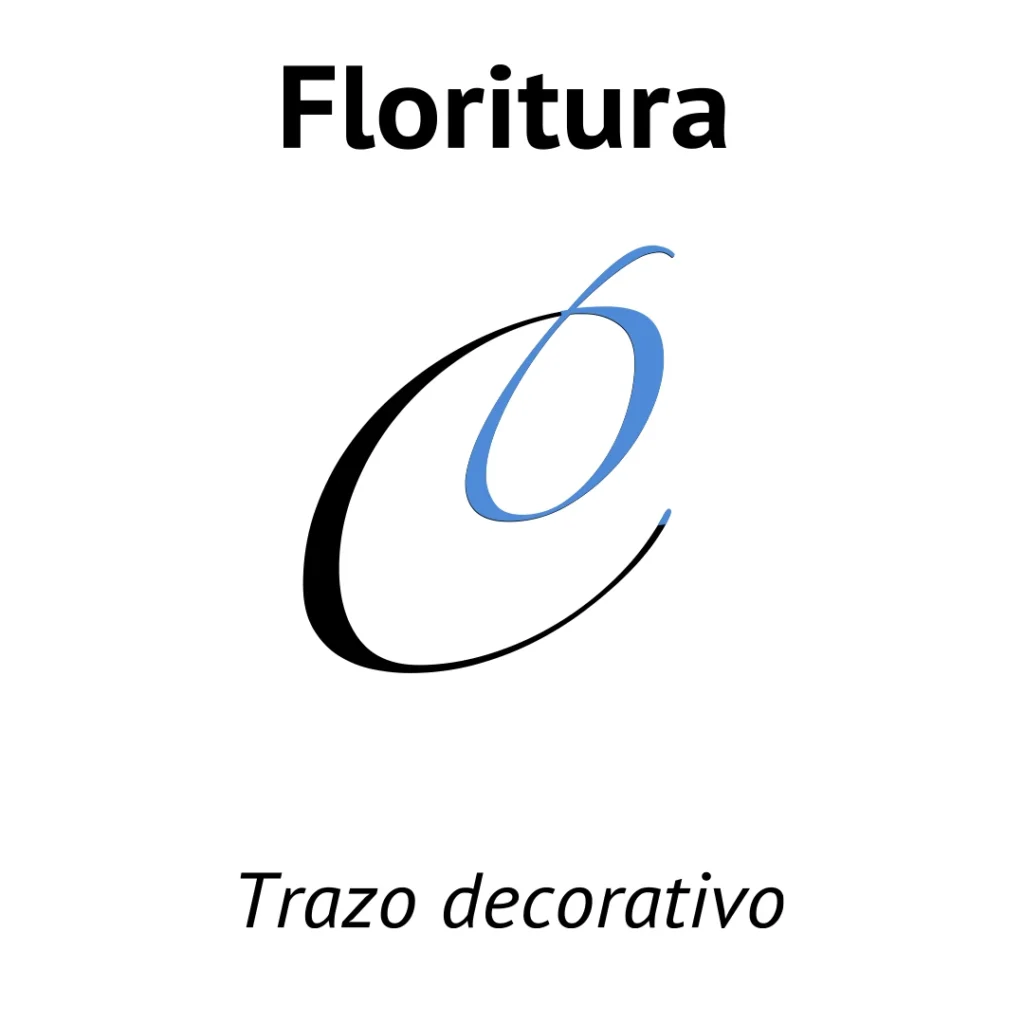
Alude a un trazo decorativo que puede tener un signo. Se relaciona con el concepto de swash, que describe un trazo alargado o exagerado de un carácter (como una cola extendida), que a veces imita una decoración floral o un adorno.